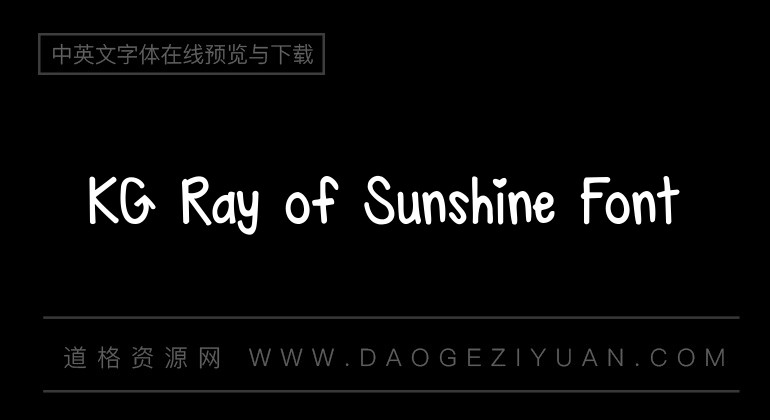
KG Ray of Sunshine Font
KG Ray of Sunshine是一种可爱的手写字体,它由设计师Kimberly Geswein创建。这个字体基于手写字母,具有自然且轻松的感觉,适用于多种项目。 它的字母形状为不规则的大小写字母,带有一些装饰性笔画,特别是在字母的末端。这种字体的颜色很鲜艳,很适合用于海报、传单、卡片等项目。 KG Ray of Sunshine字体有两种风格:正常和粗体。它还包括了大量的符号和装饰性元素,如星星、心形、花等,可以用于增强设计的可读性和吸引力。 总之,这种字体的特点是可爱、自然、轻松和充满活力,是一个适合用于多种项目的优秀选择。
KG Ray of Sunshine Font是一款非常不错的手写艺术字体,具有很好的视觉感,适合于文化类的宣传设计、商业类品牌的广告和产品包装设计以及个性化文字排版等较多场景。